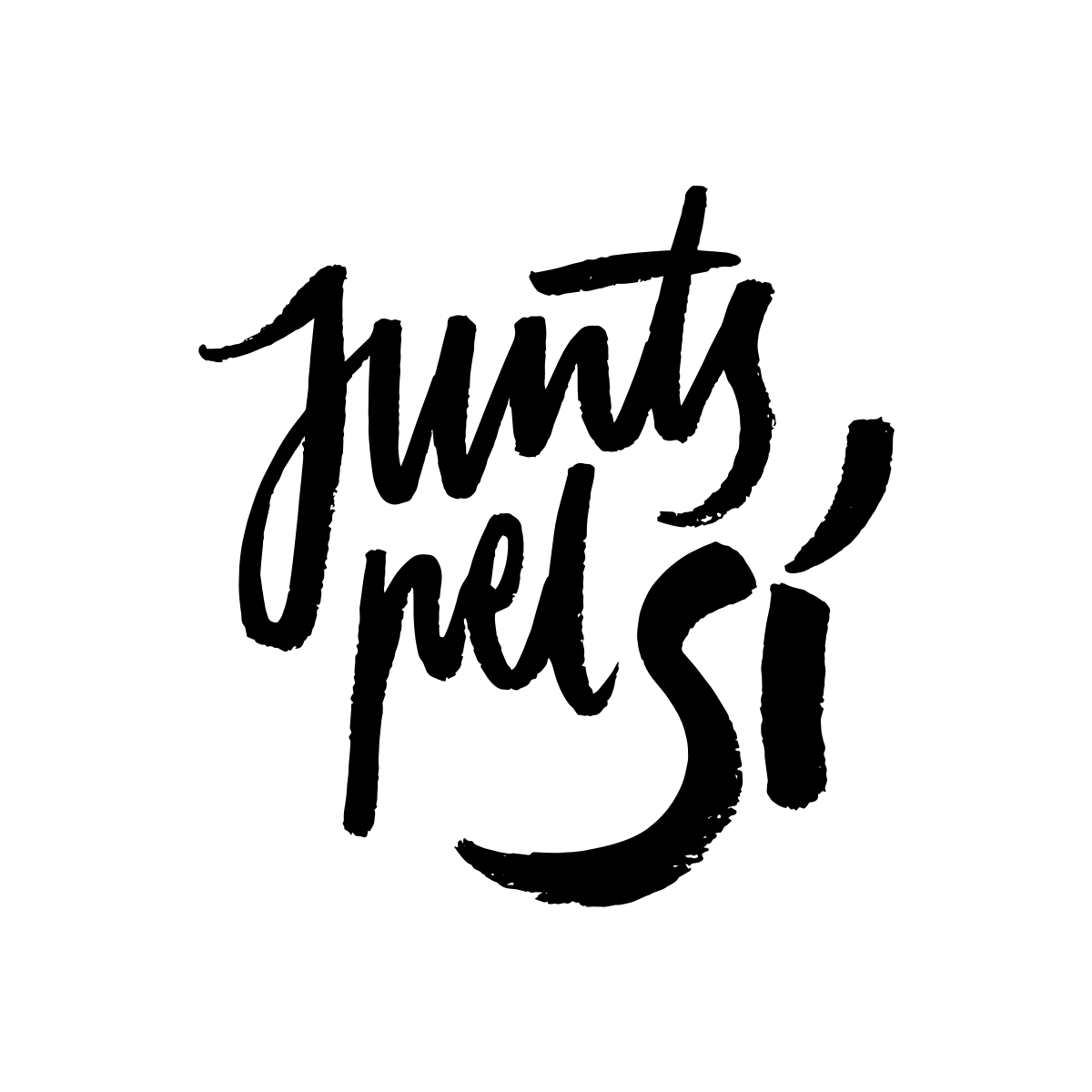
Lo preguntaba porque hay muchas tipografías que imitan una letra dibujada. Por ejemplo, la freeland, se parece muchísimo a una tipografía dibujada y a la del ejemplo que os ponía. De hecho, la freeland también es una tipo dibujada, lo único que han vectorizado letra por letra para llegar a formar la familia tipográfica entera, pensé que en este caso así como en el caso de otro logo que tienen, habían utilizado una tipo digital. Gracias
La tipografía de mi logotipo la he creado y dibujado yo
Es la misma que la de tu imagen de perfil
"Indepenfont" de la fundición Emigre.